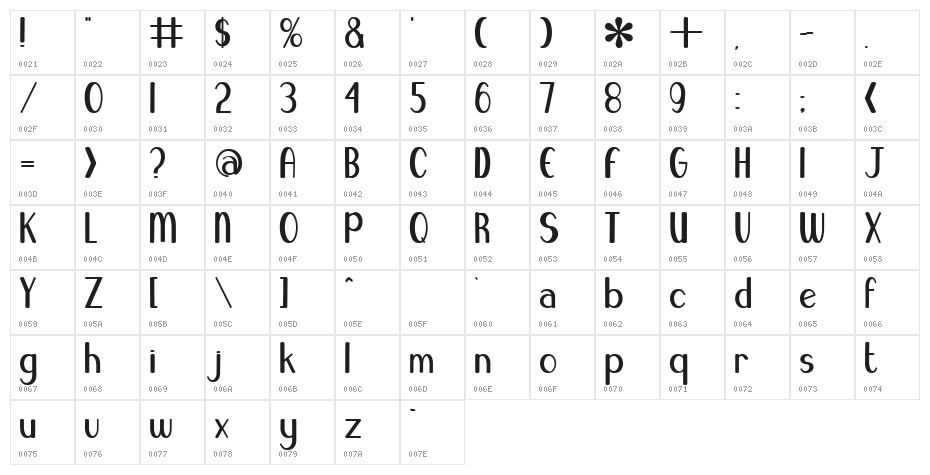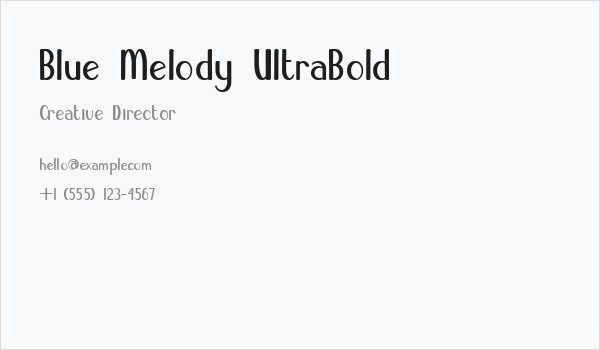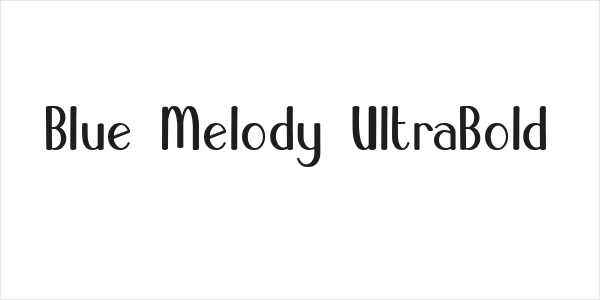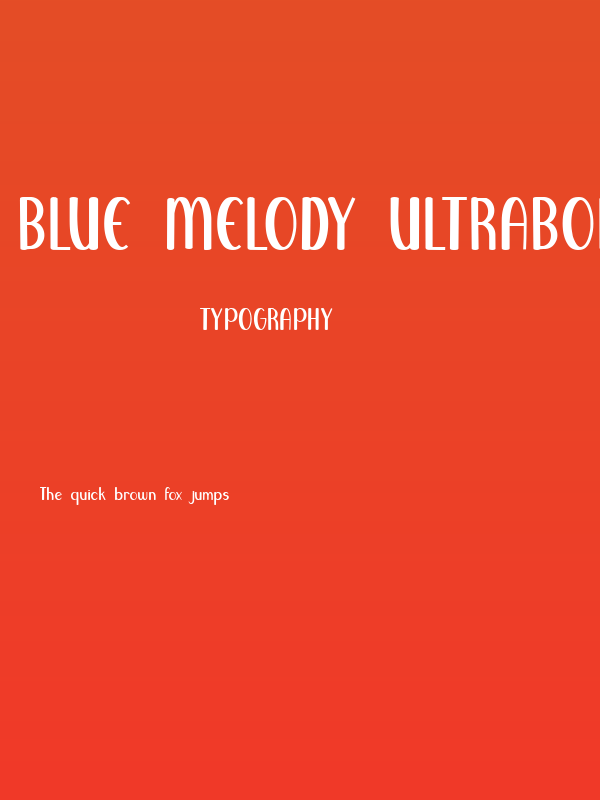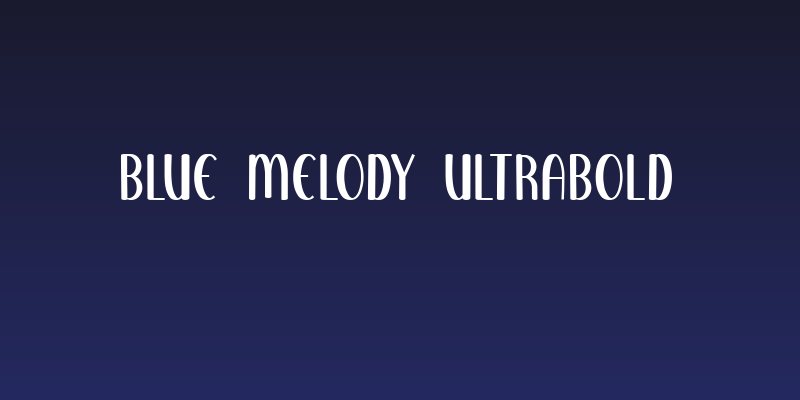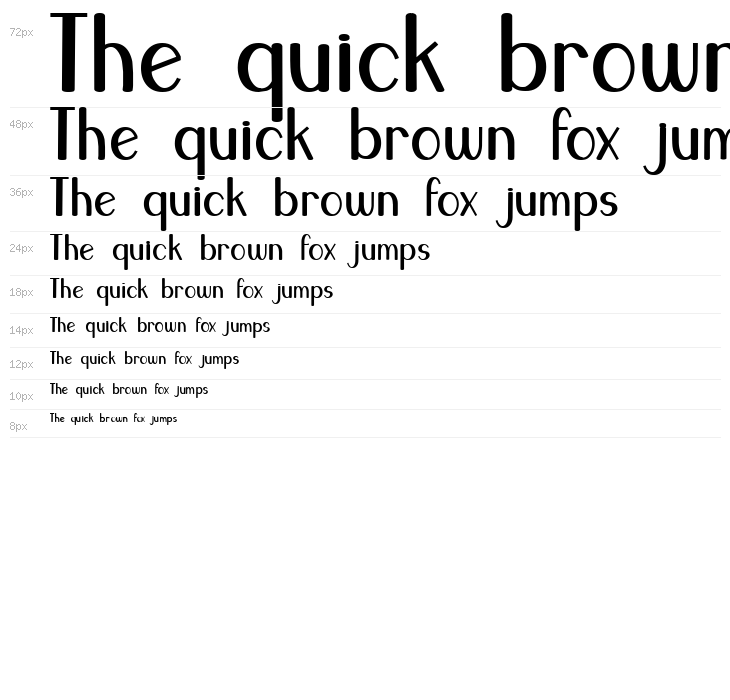
Blue Melody UltraBold Font
| Stile generale | Playful, Modern |
| Progetti proposti | Ideal for children's books, playful branding, eye-catching posters, and creative packaging designs. |